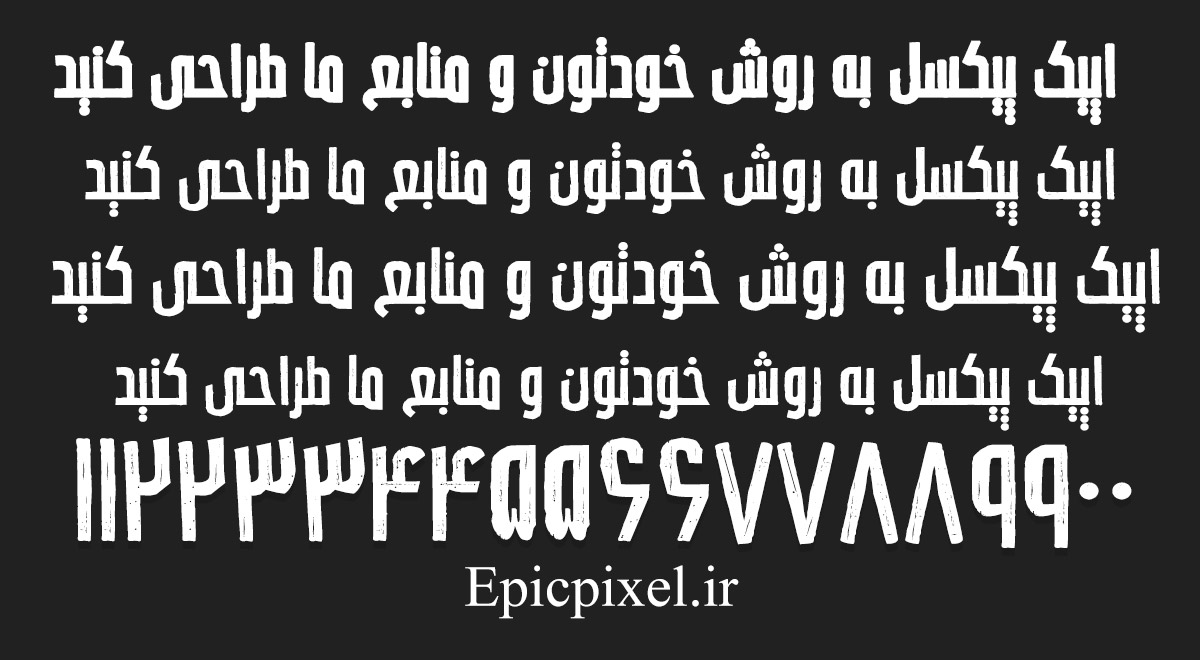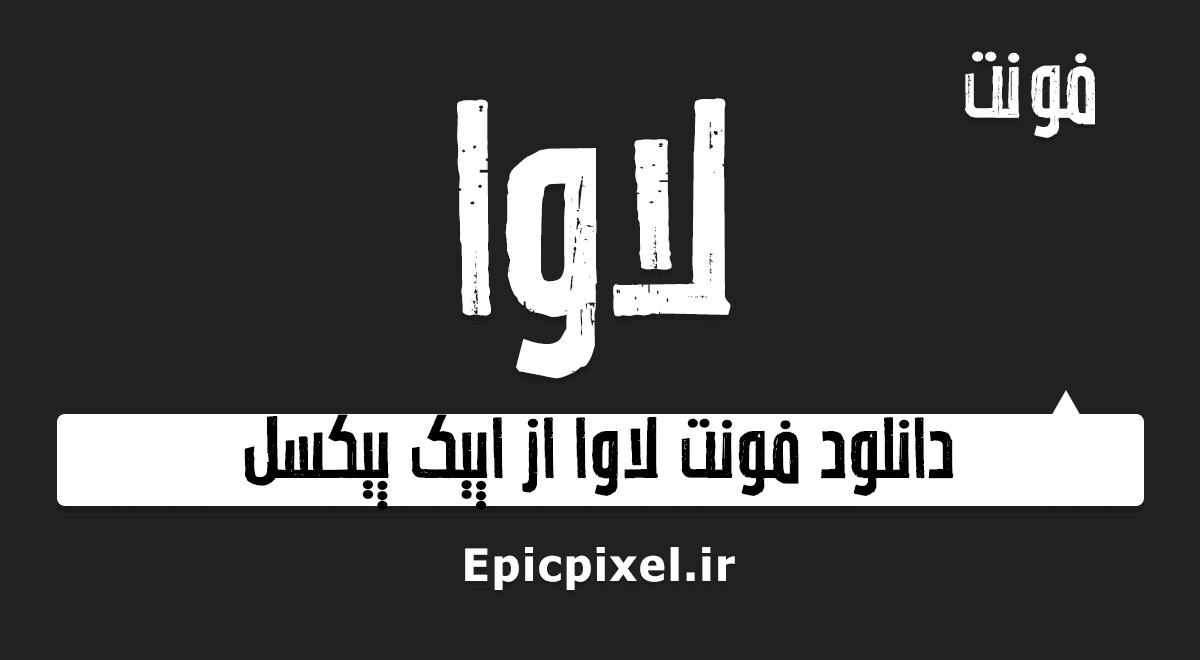
فونت لاوا فارسی عربی
دانلود فونت Lava فارسی عربی Font لاوا |
| ⭐ مجموعه فونت | دانلود فونت فارسی انگلیسی لاوا رگولار Font Lava Regular |
| ⭐ توضیحات | فونت لاوا یک فونت خفن برای کارهای گرافیکی
فونت لاوا یک فونت خفنه که میتونی برای کارهای گرافیکی و چاپی ازش استفاده کنی. این فونت هم عربی هم فارسی هم انگلیسی داره و سازندهش ابراهیم حمدی، بومبایو و عبدالله عارف هستن. این فونت چون بولد و درشته تو عکسها خیلی جلوه میکنه و میتونی برای نوشتن تابلو، لوگو، عنوان و … ازش استفاده کنی. در این مقاله بهت میگمچه خصوصیاتی تو فونت لاوا هست
این فونت خیلی جالبه شبیه اون فونت تخته چوبتون می مونه